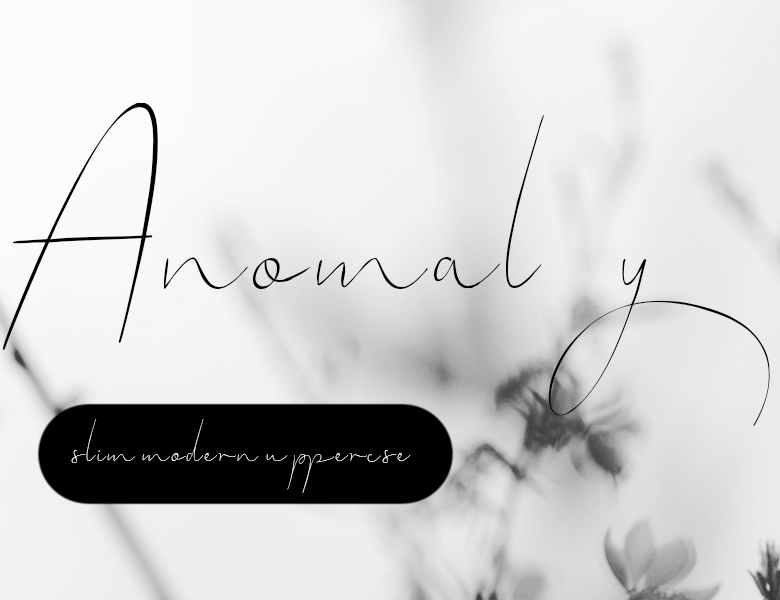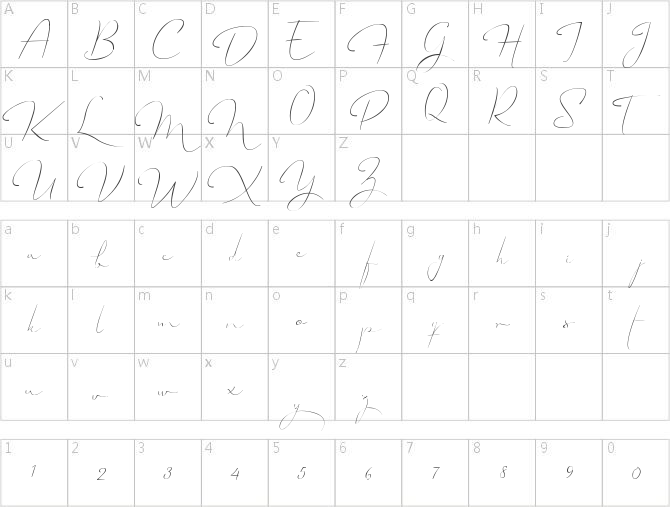
字体名称: Anomaly
Anomaly_Alternates
Anomaly_Alternates介绍
Anomaly_Alternates字体字库是一款让人赏心悦目、百看不厌的英文字体,适合各类广告和产品包装设计应用,字体大小0.06MB,格式为ttf字体,上传用户是文生电脑,作者/版权方为未知